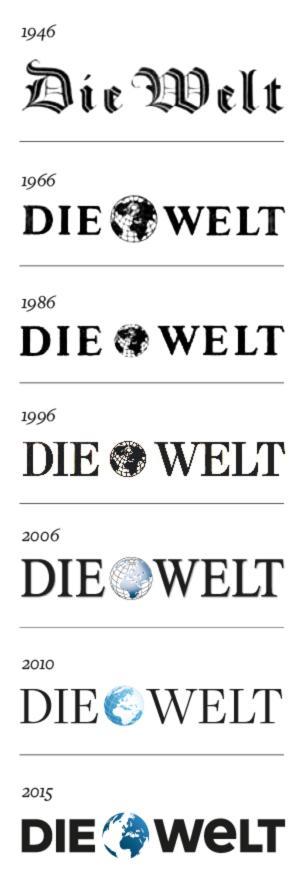
Die WELT über Schriften
Mein erster Eindruck auf der Seite war: Hä? Was hat den die Welt da für ne "Die Welt-Überschrift"? um den Titel dieses Strangs irgendwie aufzunehmen. Das logo der Welt hatte ich so noch nicht gesehen, aber sicher ist mir da nur ganz was altes im Kopf, irgendwie schade, denn ...
das ist irgendwie an mir vorbei gegangen.